Koln Studio celebra la diversidad con tipografía
Dejando de lado la bandera arcoíris, este estudio de diseño madrileño ha sido capaz de captar la esencia del World Pride.
Hace ya algunas semanas que tuvo lugar la celebración del World Pride 2017 en Madrid, ciudad que acogió la sede de los festejos este año. Unos dos millones de personas se reunieron en las calles de la capital española para celebrar el Día del Orgullo LGTBQ y la ciudad se engalanó para la ocasión. El estudio madrileñon Koln diseñó una campaña visual diametralmente alejada de la clásica bandera arcoíris, aunque igualmente atractiva.
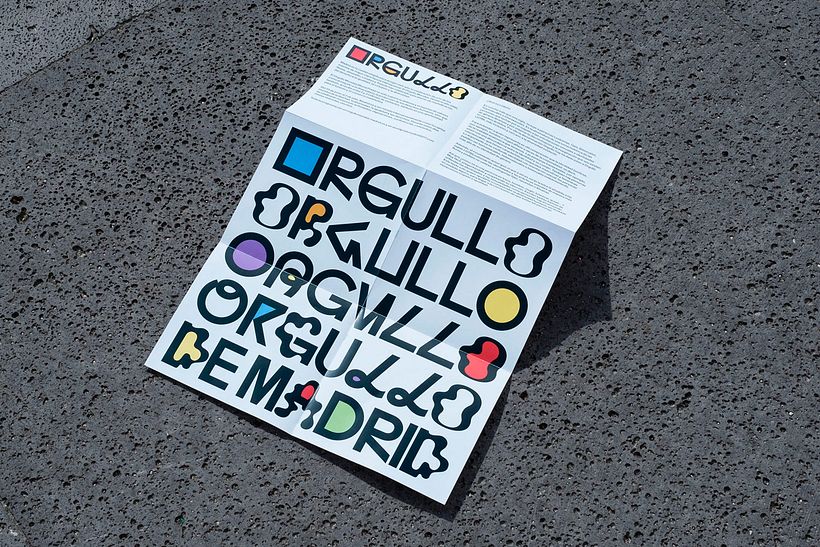
La campaña, basada casi íntegramente en elementos tipográficos, hace gala de una evidente sencillez, al tiempo que muestra la diversidad y la belleza de salirse de la norma. Las gráficas, que se han dejado ver en todo tipo de soportes alrededor de la ciudad de Madrid durante la celebración del World Pride 2017, utilizan la tipografía Lÿno, diseñada por Radim Pesko y Karl Nawrot en el año 2012.
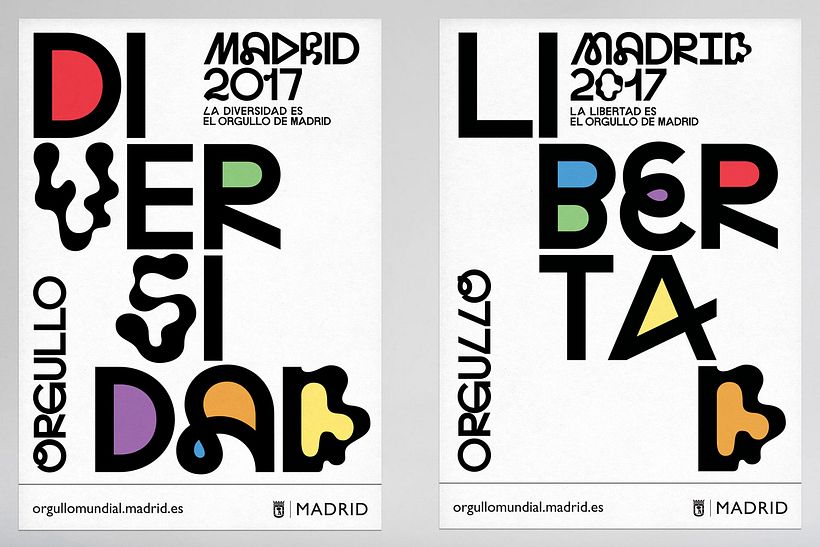
Esta tipografía cuenta con cuatro estilos diferentes basados en distintas corrientes estéticas del siglo XX: Ulys(ses 31), Stan(ley Kubrick), Jean (Arp) y Walt (Disney). Sus formas sinuosas e inesperadas, conjugadas con algunos toques de color extraídos de la clásica bandera enarbolada por el colectivo LGTBQ, convierten esta identidad gráfica en la manera ideal de representar la diversidad sin caer en los tópicos.
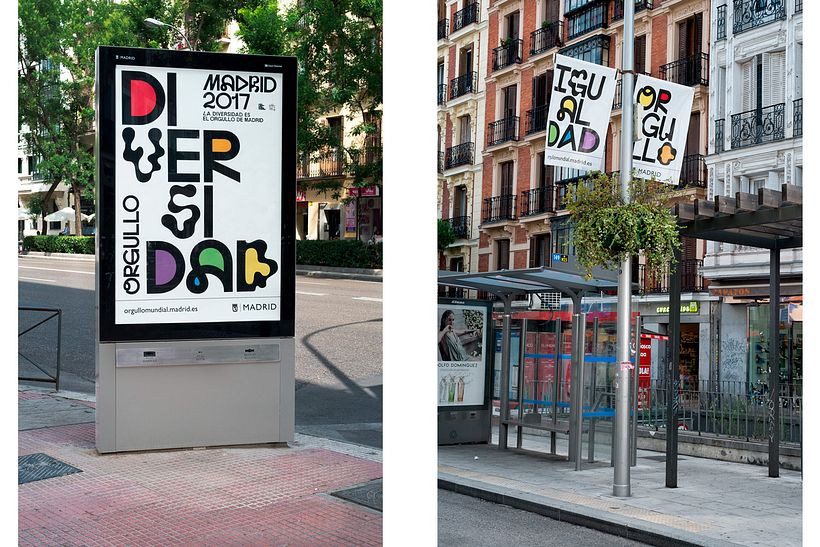
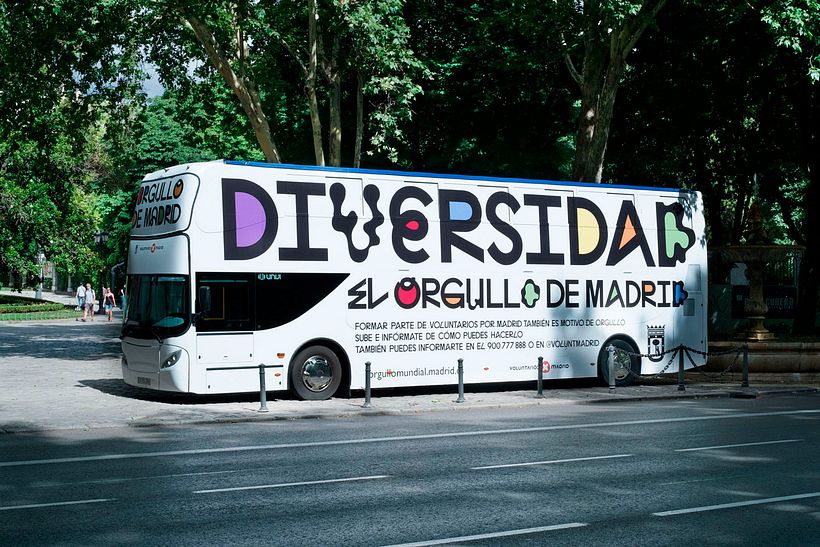
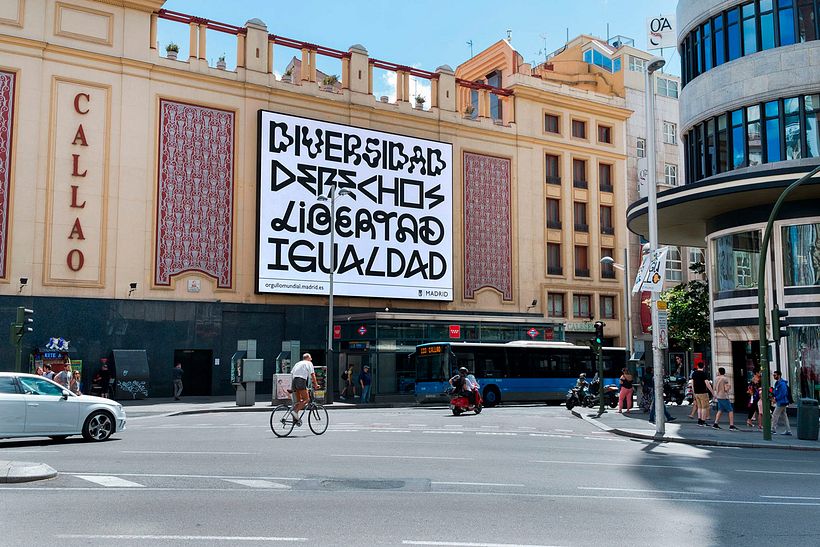
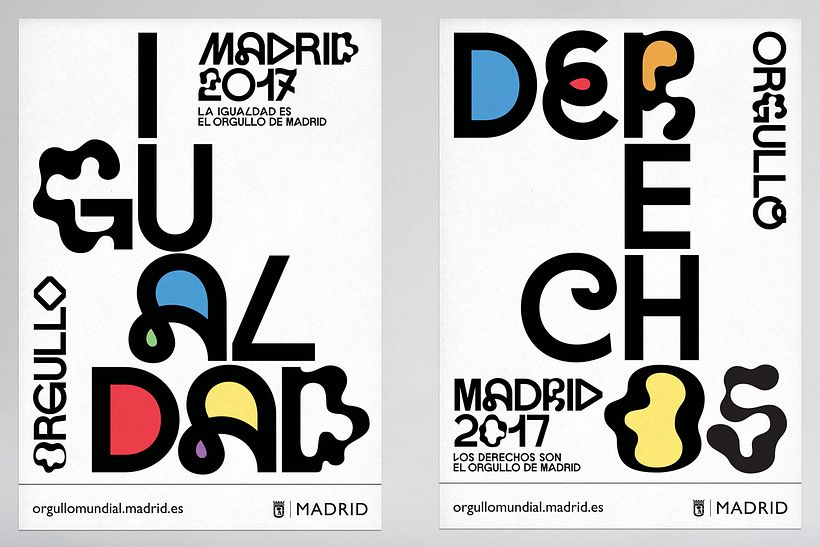
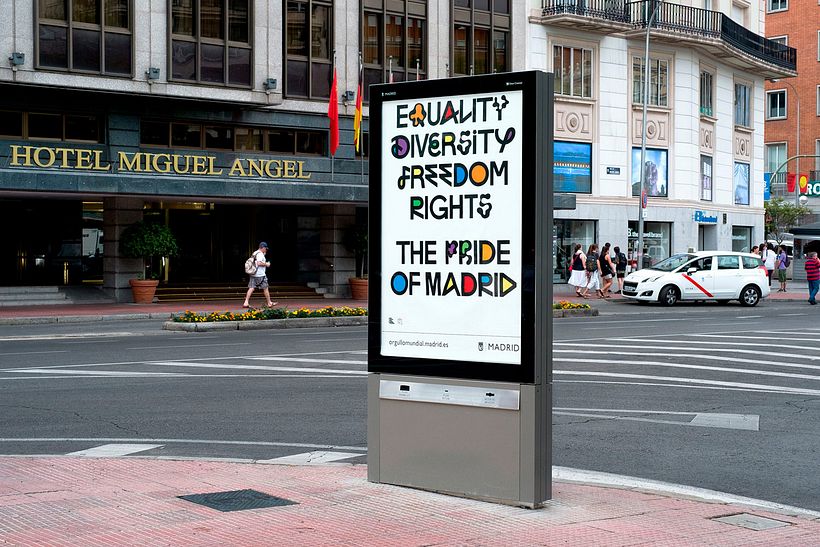
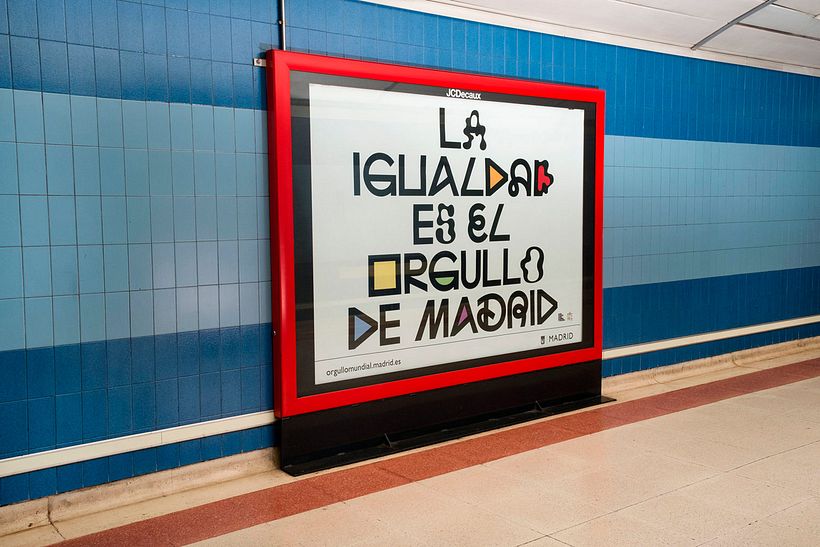
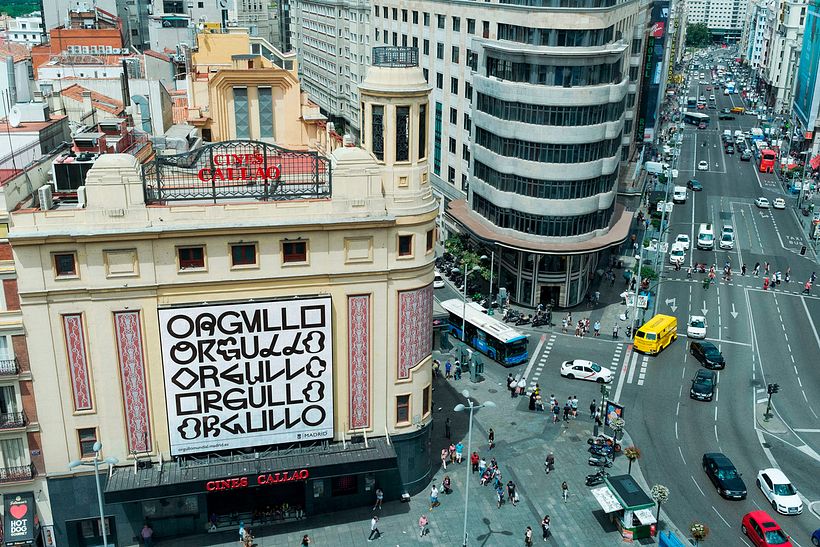
Jugando con la tipografía y con escasos toques de color, Koln Studio han sido capaces de representar la personalidad de un colectivo cuya seña de identidad está marcada por la bandera arcoíris.
Además, un proyecto que usa una tipografía contemporánea diseñada en el siglo XXI.